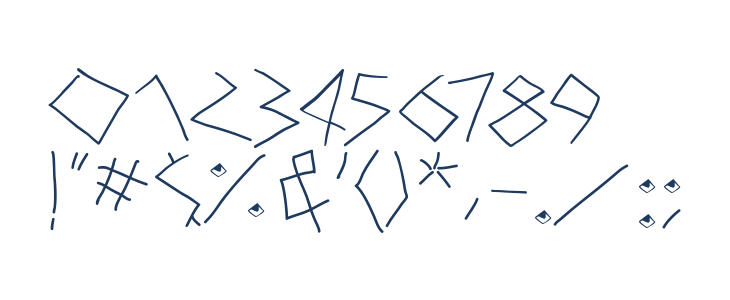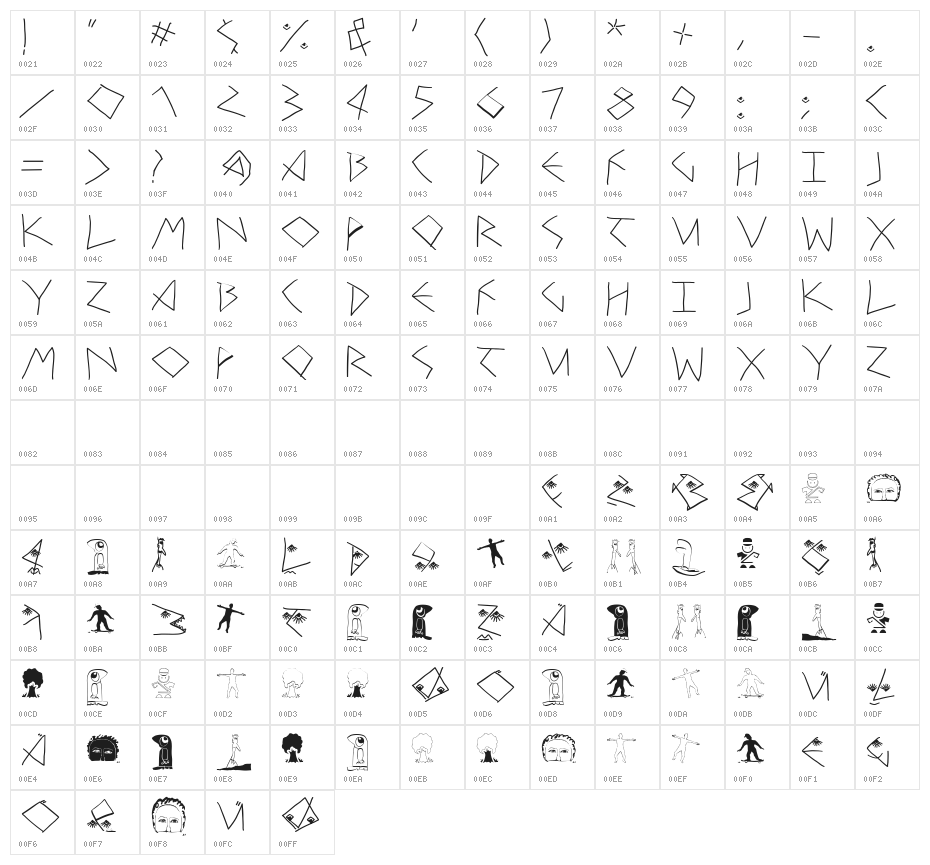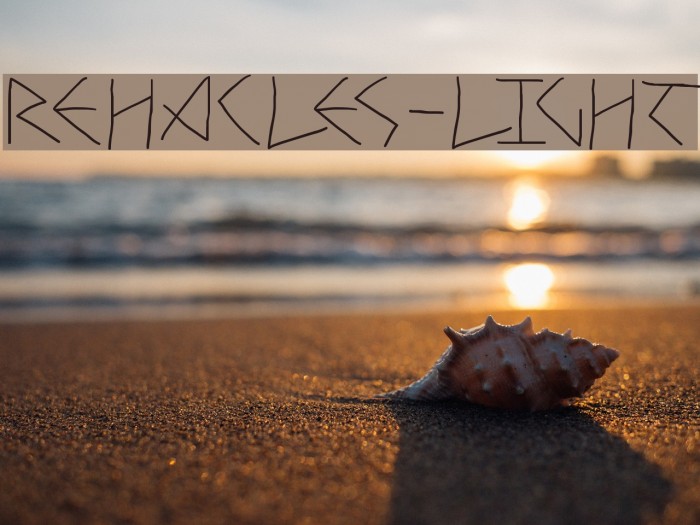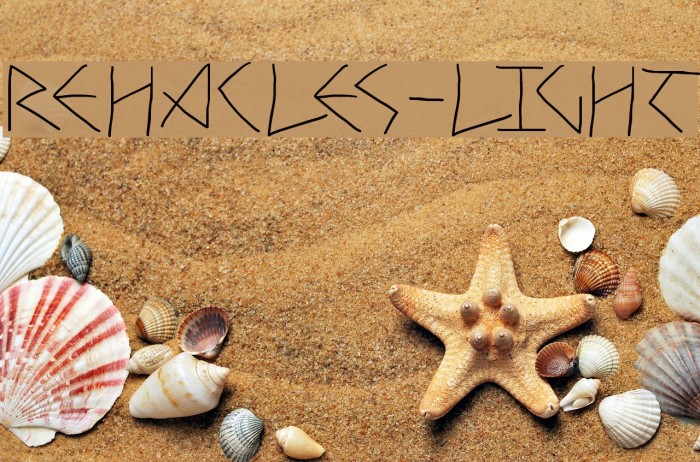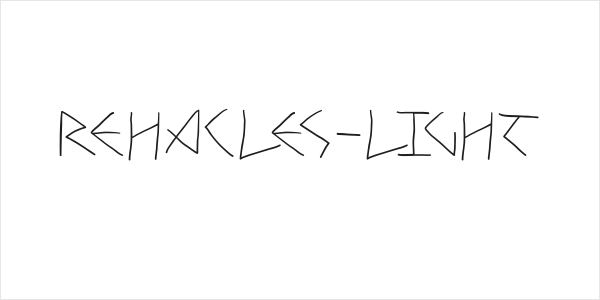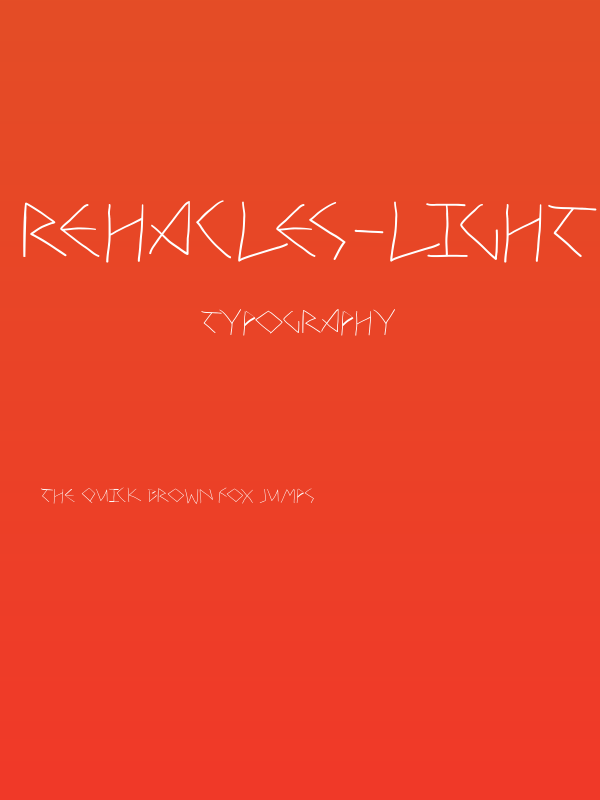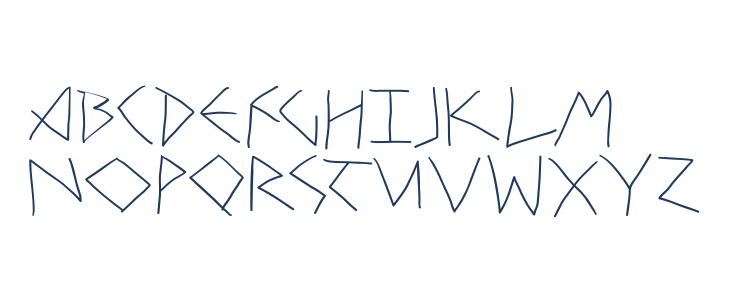
Rehacles-Light Font
| Gesamtstil | Modern, Artistic |
| Anwendungsfall | Logos, Posters, Album Covers |
| Vorgeschlagene Projekte | Ideal for artistic projects, modern branding, album covers, or any design requiring a unique, edgy look. |